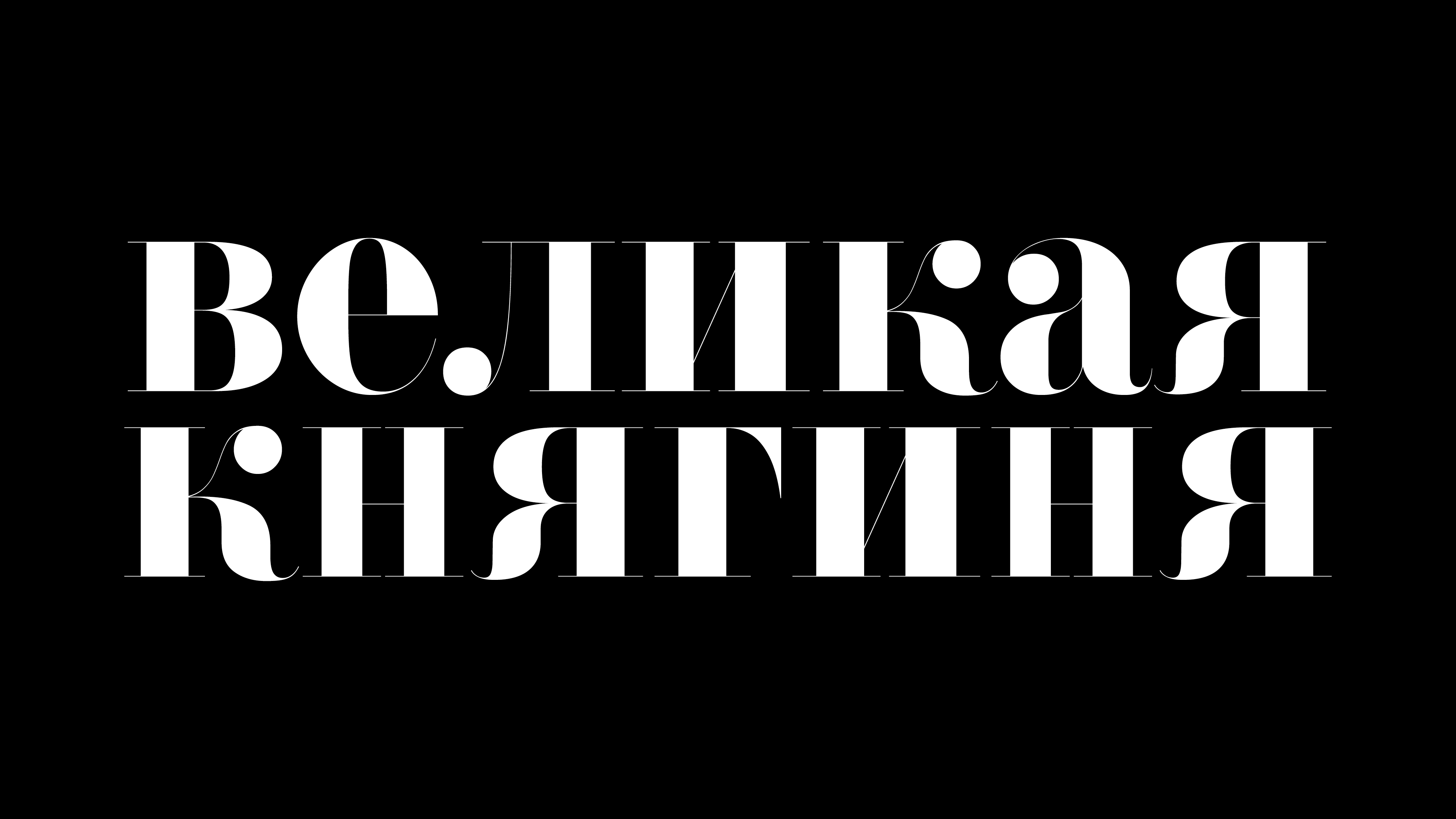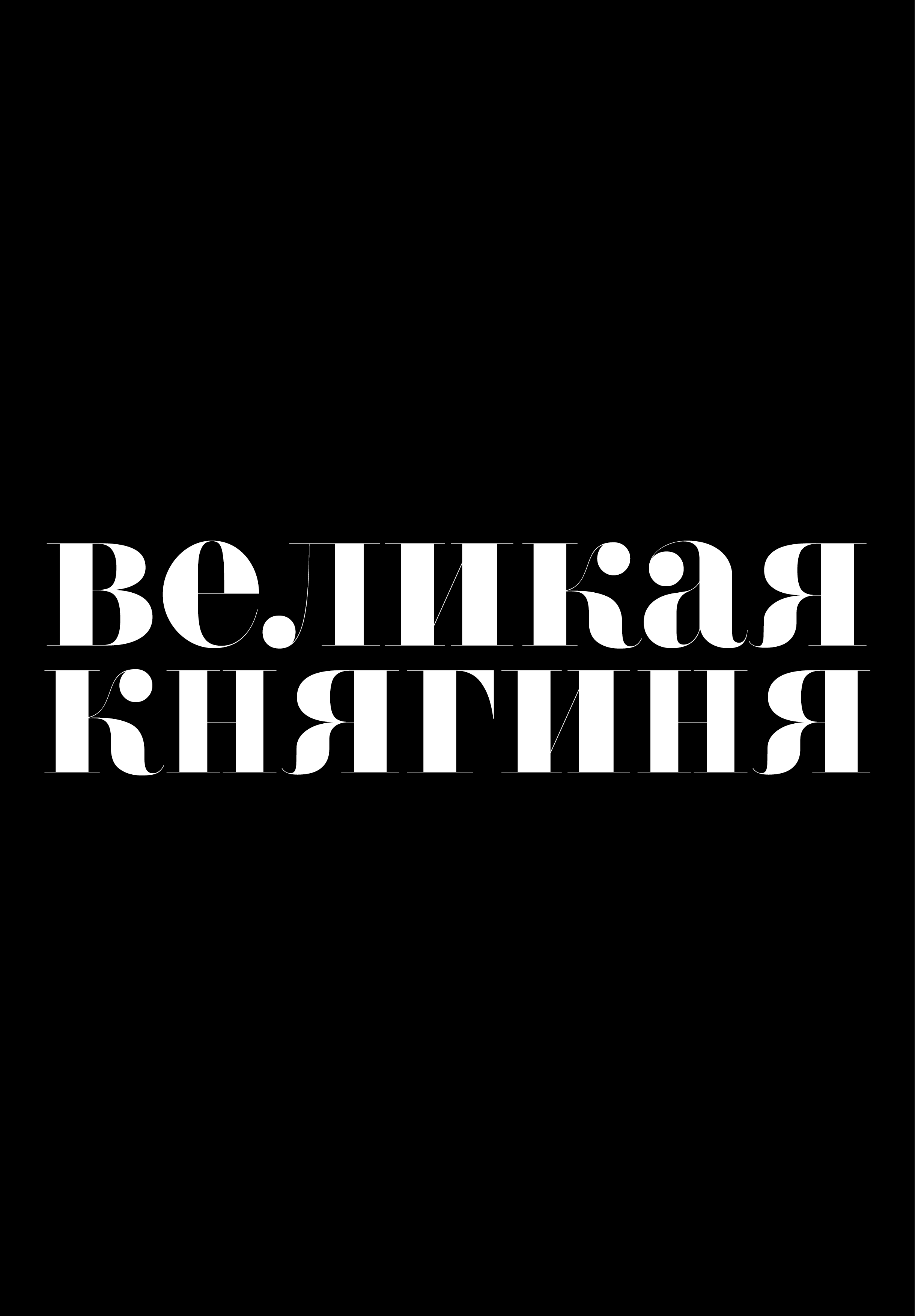
F37 Bella Cyrillic Font Sampler
Наш удостоенный наград шрифт F37 Bella, как маленькое черное платье или сшитый на заказ костюм, всегда стильный. Он сочетает в себе гламур прошлого и современную эстетику.
F37 Bella Cyrillic Text